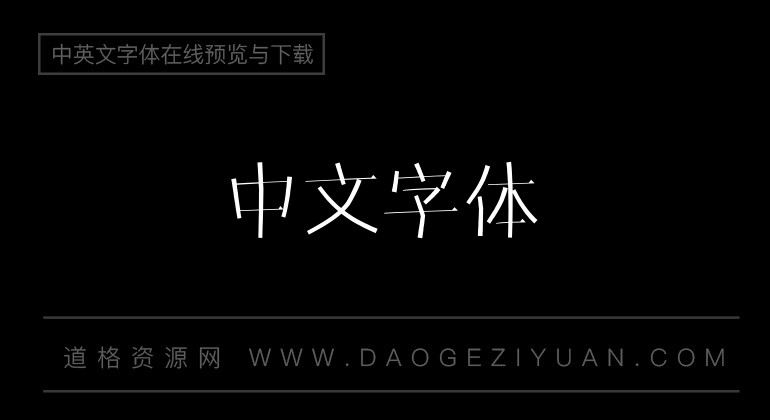
龍書慢生活空氣簡字體是一款中國傳統風格的簡體字體,由龍書設計團隊設計和開發。它以古典文人書法為藍本,結合毛筆書法和簡體漢字的特點,在細節處添加了現代元素,使它具有明快的筆劃和圓潤的線條,以及清新大氣的感覺。它適合用於各種商業廣告、報紙雜誌、書籍等印刷品,也可以用於網頁設計、網站建設、平面設計等。內容介紹
龍書慢生活空氣簡是一款非常不錯的手寫藝術字體,具有很好的視覺感,適合於文化類的宣傳設計、商業類品牌的廣告和產品包裝設計以及個性化文字排版等較多場景。